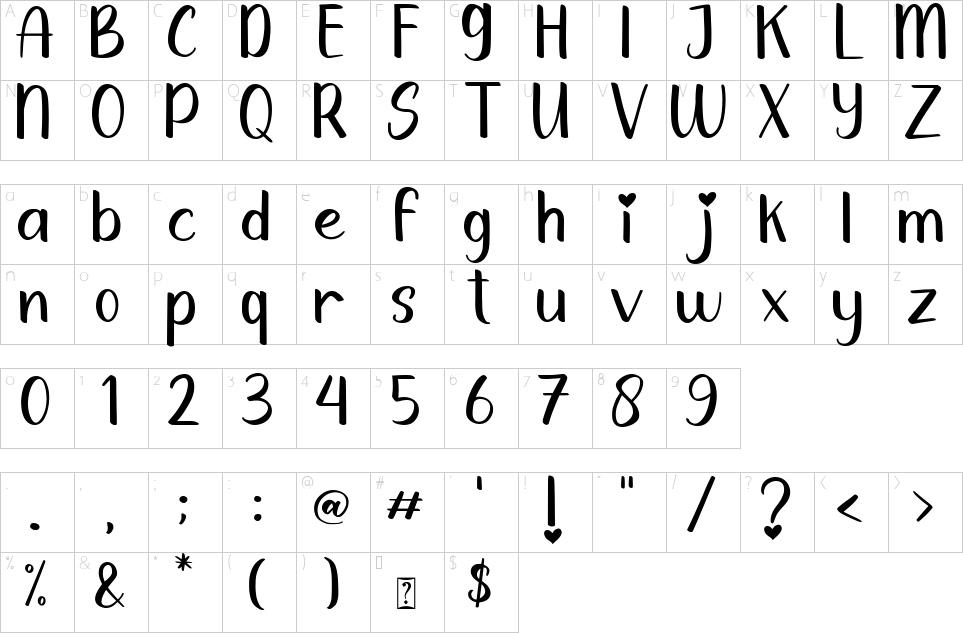
Sunny Easter Font – Fonte Grátis
Sunny Easter Font
Descubra Sunny Easter Font, uma elegante e alegre fonte gráfica para Windows e Mac. Desenhada pelo AEN Creative Studio, esta fonte traz um toque de luz e alegria às suas criações. Com seu design único e vibrante, Sunny Easter é perfeita para anúncios, rótulos de embalagens, desenhos infantis ou qualquer projeto que valorize uma atmosfera positiva e acolhedora. Com uma facilidade de uso e uma grande variedade de caracteres, Sunny Easter é uma fonte que complementa com perfeição os seus projetos. Esta fonte já foi baixada 16,271 vezes, demonstrando seu valor e qualidade. Que tal experimentar o brilho de Sunny Easter em seus projetos?
Mapa de caracteres da fonte Sunny Easter Font